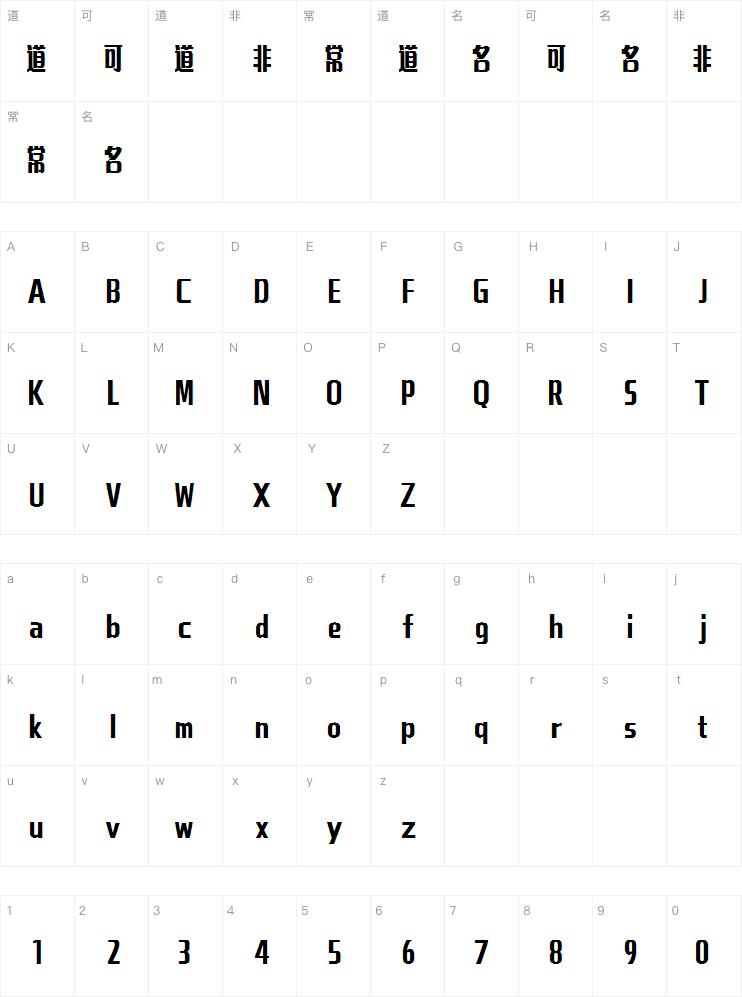
山海快乐黑w
山海快乐黑,是一款全新的字体,包含汉字9169个,符号200+个。该字体是一款综艺标题黑体字体,是一款具有强劲视觉冲击力的综艺风格标题字体。字形充实填满整个字框,造型硬朗,同时兼顾圆润性。直线与圆弧的笔画构成坚实有力,拥有宽大的中宫、粗厚且直线化的笔画设计、简洁明了的笔画尖角;字形比例按照宽高7:10的比例设计,使得字体显高;同时笔画带有圆弧装饰,使得字形更具有韵律感。该字体在综艺体的基础上做了诸多创新,使得该字体既有着流动的美感,又有着端肃的凝重,在正式用字场合落落大方,在日常使用环境中不失亲切友好,能够在保留综艺体基本特征的基础上更能适应当下时尚潮流的需要,助力各大新产品夺取标题主战场。